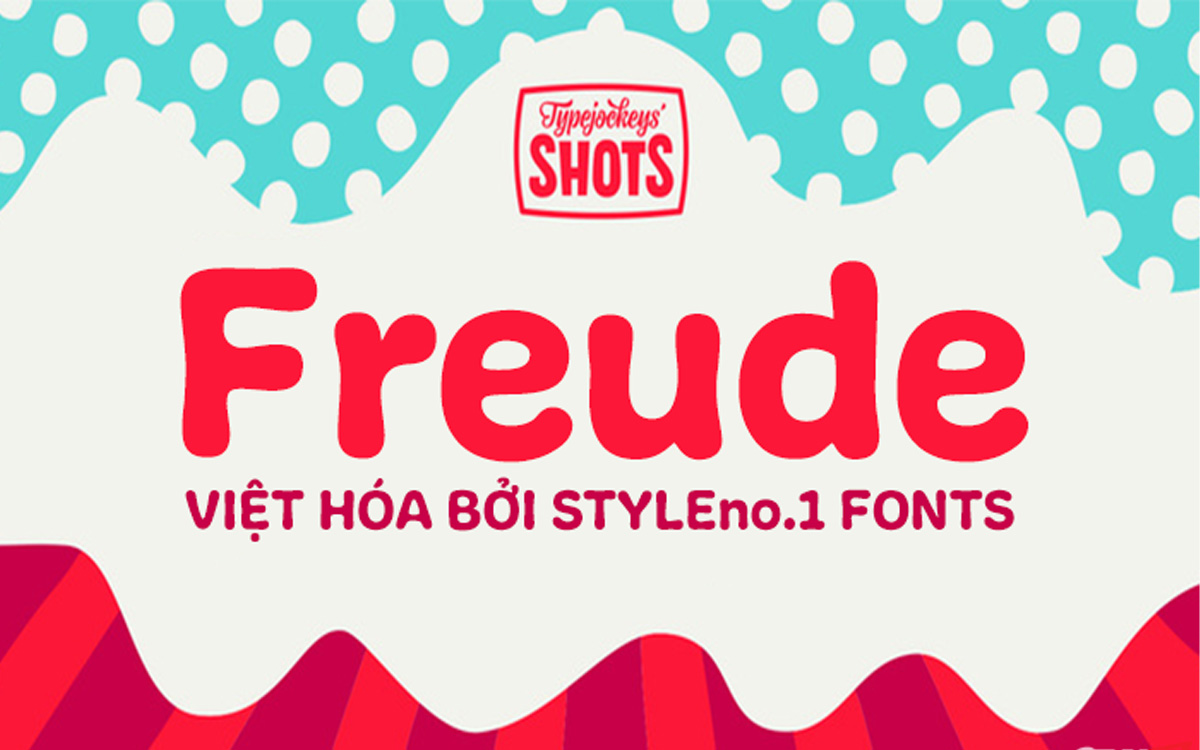
Font chữ vui vẻ, dễ thương, hoạt hình cho lĩnh vực trẻ em, đồ ăn, fodd, cute SVN-Freude
Trong thế giới thiết kế đồ họa hiện đại, việc lựa chọn một phông chữ phù hợp không chỉ dừng lại ở khả năng hiển thị thông tin mà còn đóng vai trò cốt lõi trong việc truyền tải cảm xúc và định hình phong cách thương hiệu. Font chữ SVN-Freude ra đời như một giải pháp hoàn hảo mang đến làn gió mới ngập tràn niềm vui, sự hồn nhiên và nét ngộ nghĩnh cho mọi sản phẩm sáng tạo. Nếu bạn đang tìm kiếm một bộ font mang phong cách hoạt hình, thân thiện dành riêng cho ngành hàng trẻ em và lĩnh vực ẩm thực F&B, SVN-Freude chắc chắn là sự lựa chọn không thể bỏ qua.
SVN-Freude – Font Chữ Vui Vẻ, Dễ Thương, Hoạt Hình Độc Đáo Cho Lĩnh Vực Trẻ Em Và Thiết Kế Đồ Ăn Cute
Thiết kế dành cho đối tượng thiếu nhi cũng như ngành dịch vụ ăn uống (Food & Beverage) luôn đòi hỏi tính sáng tạo vượt giới hạn, màu sắc bắt mắt cùng ngôn ngữ hình ảnh có khả năng thu hút sự chú ý ngay từ cái nhìn đầu tiên. Người tiêu dùng nhỏ tuổi và các tín đồ đam mê ẩm thực thường bị lôi cuốn bởi những đường nét mềm mại, hóm hỉnh và tràn đầy sức sống. Font chữ SVN-Freude đáp ứng trọn vẹn những tiêu chuẩn khắt khe này nhờ sự kết hợp tinh tế giữa phong cách hoạt hình (cartoon style) và tính ứng dụng thực tế vô cùng cao.
SVN-Freude là bản Việt hóa chỉn chu, giúp các nhà thiết kế tại Việt Nam dễ dàng sáng tạo các nội dung tiếng Việt có dấu mà không gặp phải tình huống lỗi font hay mất đi tính thẩm mỹ nguyên bản. Với cấu trúc nét chữ dày dặn, các góc bo tròn duyên dáng cùng nhịp điệu chữ tự do, sinh động, bộ font này có khả năng biến mọi khẩu hiệu (slogan), tiêu đề sách, biển hiệu hay bao bì sản phẩm trở nên nổi bật, cuốn hút và ngập tràn năng lượng tích cực.
1. Nét chữ bo tròn, ngộ nghĩnh và lan tỏa năng lượng tích cực
Điểm đặc trưng nổi bật nhất của SVN-Freude chính là ngôn ngữ tạo hình ngộ nghĩnh. Các nét chữ được thiết kế chắc chắn nhưng không hề thô cứng nhờ vào việc xử lý bo tròn tỉ mỉ ở các đầu nét và góc cạnh. Sự thay đổi linh hoạt về tỷ lệ giữa các chữ cái tạo nên nhịp điệu nhún nhảy vui tươi, gợi liên tưởng đến những nhân vật hoạt hình đáng yêu hay các món bánh ngọt ngào. Yếu tố thị giác độc đáo này giúp phông chữ lan tỏa cảm xúc vui vẻ, tạo sự gần gũi và rút ngắn khoảng cách giữa thương hiệu với khách hàng mục tiêu.
2. Tối ưu hóa hoàn hảo cho ngành F&B, quán ăn và thực phẩm trẻ em
Trong ngành công nghiệp đồ ăn và thức uống (Food & Beverage), yếu tố thị giác đóng vai trò quyết định đến cảm giác ngon miệng và hành vi mua hàng. SVN-Freude cực kỳ phù hợp để ứng dụng trên các thiết kế menu, bảng hiệu quán trà sữa, tiệm bánh kem, nhà hàng thức ăn nhanh hay bao bì đồ ăn vặt. Đường nét mập mạp, “béo tròn” của font chữ tạo cảm giác đầy đặn, hấp dẫn và kích thích vị giác mạnh mẽ. Đối với các dòng sản phẩm dành riêng cho trẻ em như sữa, bánh kẹo, đồ chơi hay sách truyện thiếu nhi, SVN-Freude mang lại cảm giác thân thiện, an toàn và vô cùng cuốn hút đối với các bé.
3. Hỗ trợ tiếng Việt chuẩn xác cùng bộ ký tự phong phú
Một trong những rào cản lớn nhất của các nhà thiết kế khi sử dụng font chữ nước ngoài là vấn đề lỗi hệ thống dấu tiếng Việt hoặc dấu thanh bị đặt lệch vị trí làm mất cân đối thẩm mỹ. SVN-Freude đã được Việt hóa một cách công phu và chuẩn xác, đảm bảo đầy đủ các dấu thanh (sắc, huyền, hỏi, ngã, nặng) cũng như các ký tự đặc trưng của tiếng Việt (â, ă, ê, ô, ơ, ư, đ). Sự đồng bộ tuyệt đối về nét vẽ giữa dấu và chữ giúp văn bản đạt độ cân đối hoàn hảo về khoảng cách (kerning) và khoảng cách dòng (leading), mang lại vẻ đẹp chuyên nghiệp cho toàn bộ ấn phẩm.
4. Khả năng ứng dụng linh hoạt trên đa dạng chất liệu truyền thông
Không chỉ giới hạn trong các thiết kế in ấn truyền thống như poster, banner, tờ rơi hay bao bì sản phẩm, SVN-Freude còn phát huy sức mạnh vượt trội trên các nền tảng truyền thông kỹ thuật số. Bạn có thể dễ dàng ứng dụng bộ font này để tạo tiêu đề ấn tượng cho ảnh thu nhỏ (thumbnail) YouTube, bài đăng mạng xã hội (Facebook, Instagram, TikTok), banner quảng cáo trên các sàn thương mại điện tử hay giao diện ứng dụng dành cho trẻ em. Tính nhận diện cao của font giúp thông điệp của bạn luôn nổi bật giữa vô số nội dung trên môi trường số.
5. Tương thích xuất sắc với các phần mềm thiết kế đồ họa
Font chữ SVN-Freude được đóng gói ở các định dạng chuẩn quốc tế (OTF/TTF), cho phép người dùng dễ dàng cài đặt chỉ với một vài thao tác đơn giản và hoạt động mượt mà trên cả hai hệ điều hành phổ biến là Windows và macOS. Bộ font tương thích hoàn hảo với tất cả các phần mềm thiết kế đồ họa hàng đầu hiện nay như Adobe Photoshop, Adobe Illustrator, Adobe InDesign, CorelDraw, Canva, cho đến các ứng dụng biên tập video như Premiere Pro hay After Effects. Điều này giúp tối ưu hóa tiến độ công việc và gia tăng hiệu suất sáng tạo cho các designer.
Gợi Ý Phối Màu Và Bố Cục Khi Sử Dụng Font Chữ SVN-Freude
Được đánh giá là một font chữ mang đậm tính nghệ thuật và trang trí, SVN-Freude sẽ phát huy tối đa vẻ đẹp nếu được kết hợp đúng cách trong không gian thiết kế. Dưới đây là một số mẹo nhỏ từ chuyên gia giúp bạn sáng tạo nên những ấn phẩm bắt mắt nhất:
• Lựa chọn bảng màu tươi sáng: SVN-Freude cực kỳ ăn ý với các gam màu pastel ngọt ngào (hồng phấn, xanh mint, vàng bơ, tím nhạt) hoặc các sắc thái màu rực rỡ (cam tươi, đỏ dâu, xanh lá mạ). Việc sử dụng màu sắc phù hợp sẽ tôn lên tinh thần “cute” và phong cách hoạt hình sinh động của bộ font.